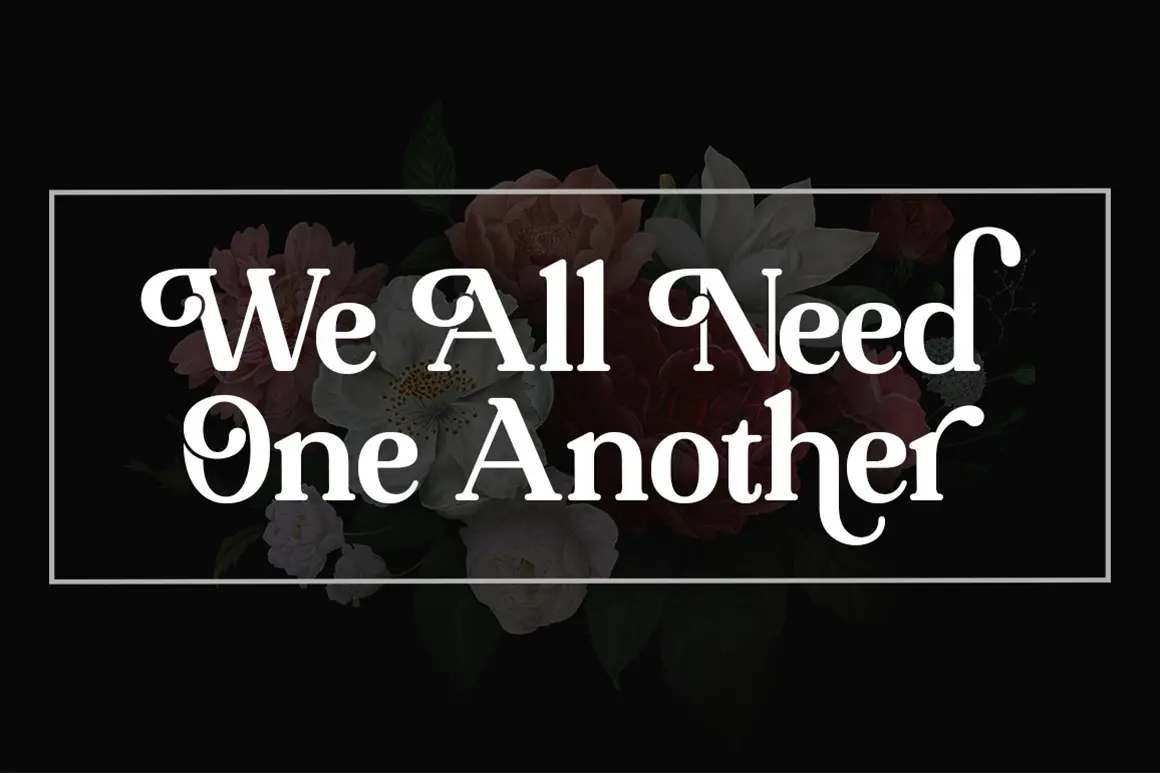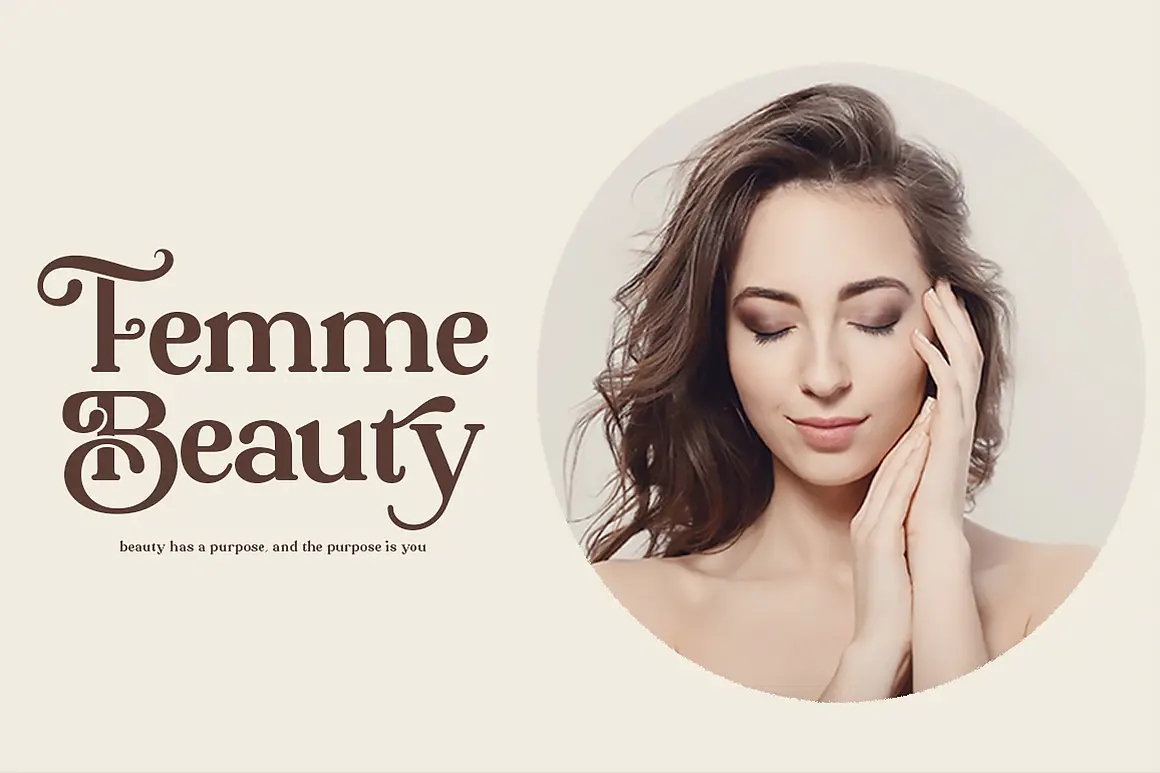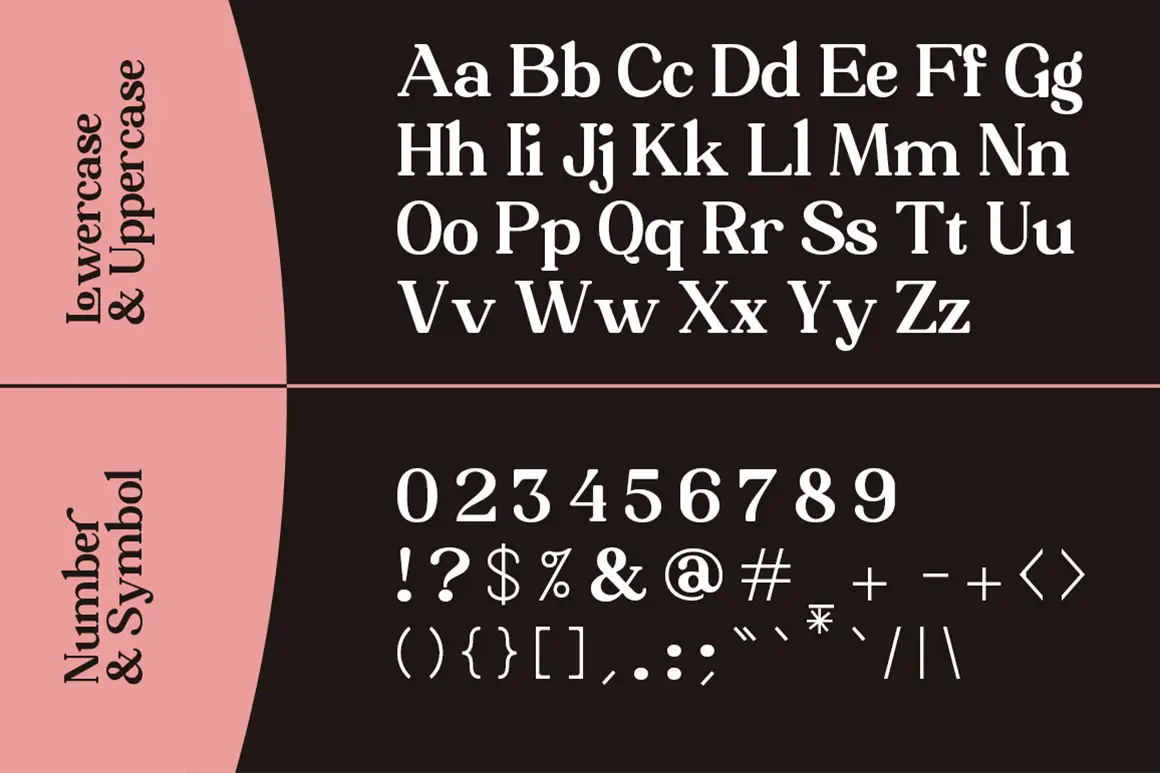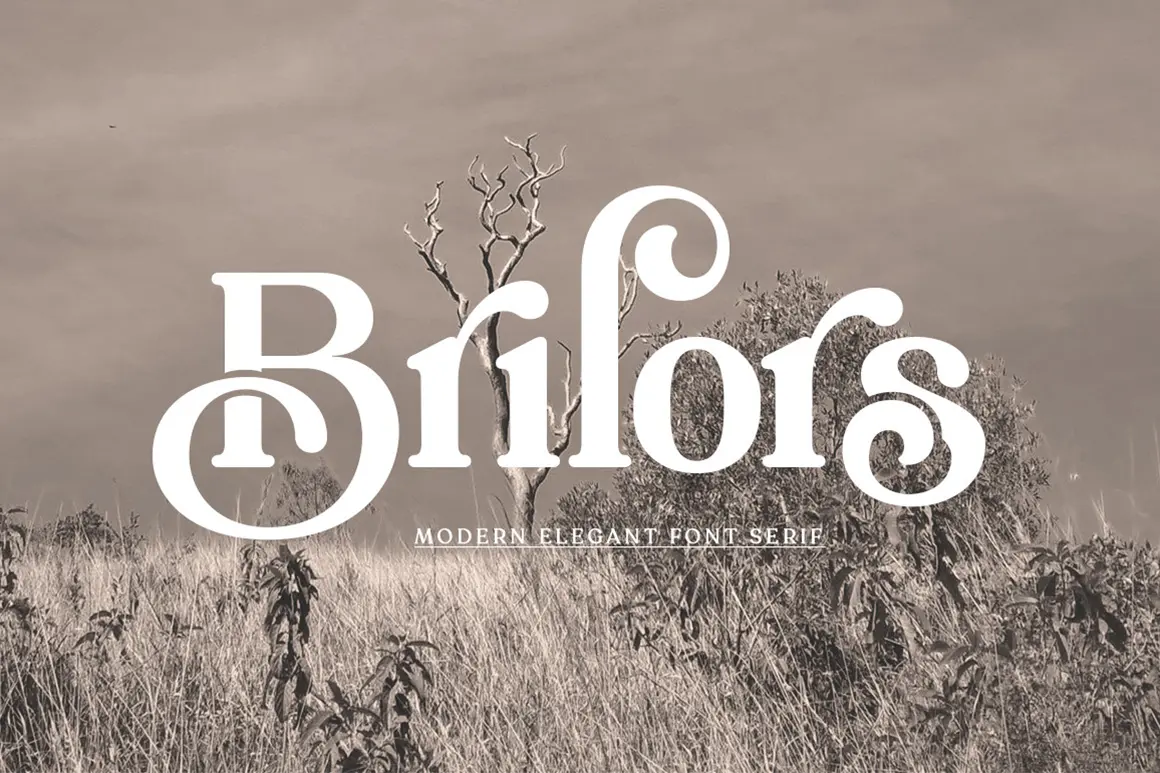
فونت سریف شیک و ظریف رایگان
فونت Brilors یک فونت سریف زیبا و استایلدار است که با طراحی ظریف و حرفهای، جلوهای خاص به پروژههای شما میبخشد. این فونت با جزئیات دقیق و منحنیهای جذاب، انتخابی عالی برای طراحیهای مدرن و کلاسیک است.
⭐ ویژگیهای محصول:
- سبک: Serif Font – فونت سریف کلاسیک و مدرن
- طراحی: شیک، ظریف و حرفهای
🎯 موارد استفاده:
- طراحی لوگوهای خاص و هنری
- تیترها و سرتیترهای تبلیغاتی جذاب
- کارتهای تبریک و دعوتنامههای شیک
- پوسترها و مجلات ادیتوریال
- بستهبندی محصولات لوکس و خلاقانه